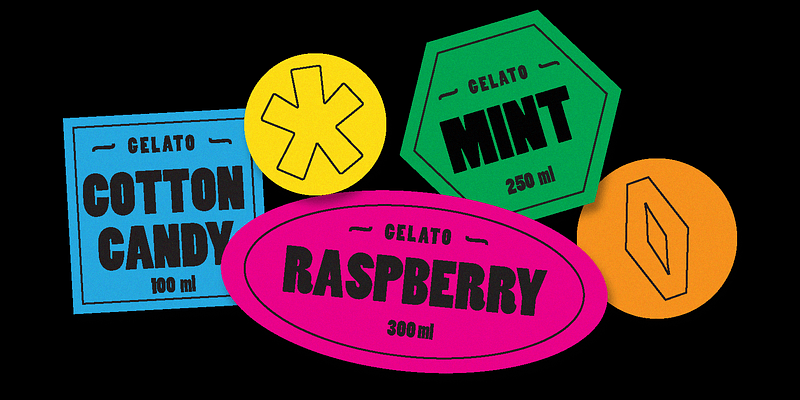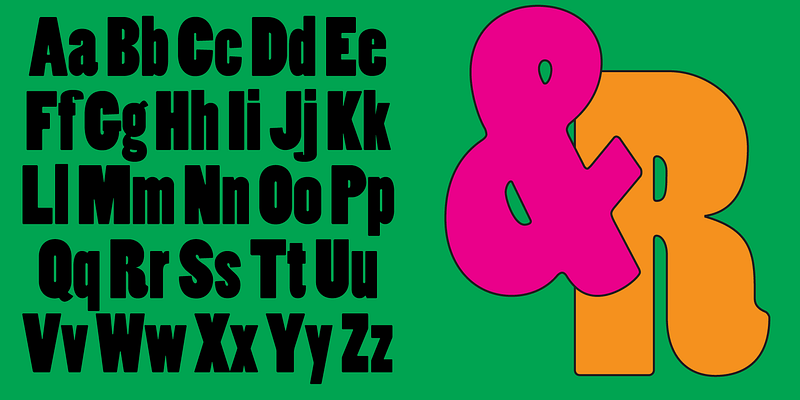
「Poplar」は 1990 年に Barbara Lind が Adobe Wood Type シリーズのためにデザインした Adobe Originals 書体です。ゴシック体のコンデンス体である「Poplar」は、1830 年に発行された William Leavenworth による書体見本帳の現存する 1 冊を撮影した Rob Roy Kelly の写真に基づいてデザインされました。Leavenworth は類まれな芸術的才能の持ち主で、彼の手による細いスリットのような字形のふところは、19 世紀に発表されたこの種の木活字では唯一のものでした。「Poplar」は優れたディスプレイ書体であり、シンプルで幅広い用途に使用できます。